산돌네오시리즈_2.고딕네오와 명조네오
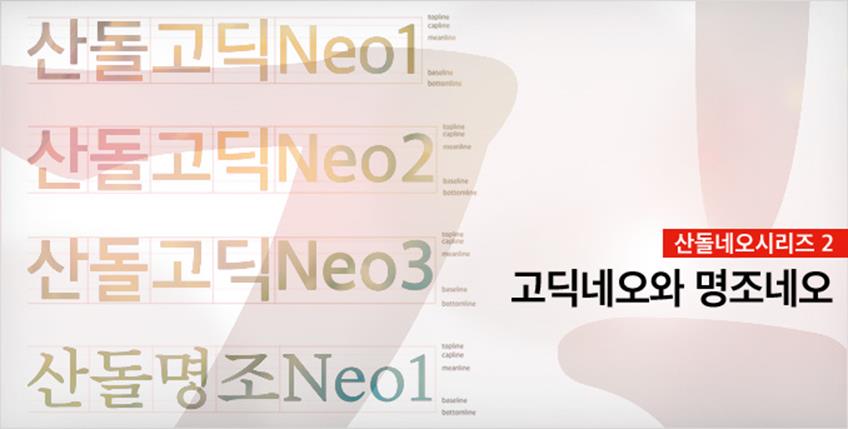
산돌고딕네오1의 컨셉과 특징
산돌고딕네오1은 탈네모가 아닌 네모틀의 한글 활자체이지만 초성, 중성, 종성의 자소들이 네모틀 내부에서 좀 더 자유로워진 형태를 갖추고 있다. 모듈 내부의 검은 글자와 흰 공간이 가지런하게 안배되어 기존 산돌고딕의 고전적인 모습보다 현대적인 이미지를 담고 있다. 또한, 산돌고딕네오1은 편집디자이너들의 요구에 맞추어 정교한 조판을 위한 다양한 웨이트를 제공한다. 그로 인해 합성글꼴 사용시 보다 균정한 지면의 색채감 제공이 가능하다. 다양해진 인쇄환경에 따라 미세한 차이를 고려하여 웨이트를 적용하면 보다 높은 품질의 결과물을 얻을 수 있도록 한 것이다.
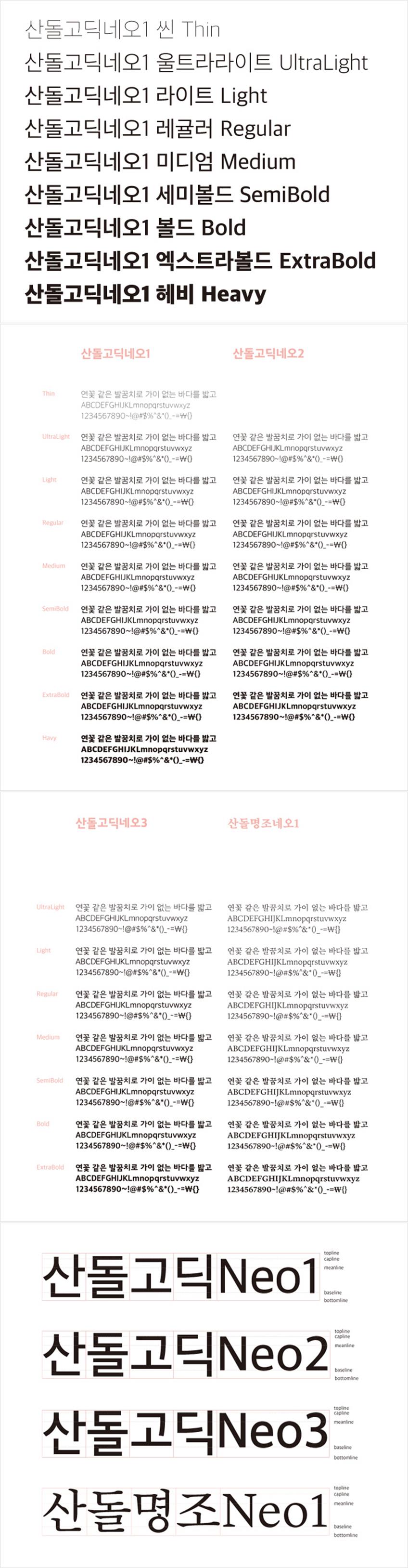
산돌네오시리즈는 산돌고딕네오1, 고딕네오2, 고딕네오3, 명조네오1으로 구성되어 있다.
산돌고딕네오1에는 영국 유력일간지 <The Guardian>의 Guardian Sans Headline을 개발한 커머셜 타입(Commercial Type)으로부터 정식 라이선스를 획득하여 개발한 ‘산돌가디언산스’가 라틴 알파벳 폰트로 포함되어 있다. 산돌가디언산스는 가디언산스 활자체 본래의 성격은 유지하되 한글의 구조와 골격에 잘 어울리도록 각각의 사이즈와 자간을 조정해 시각적 균등감과 조화를 이루어 냈고, 한글과 라틴 알파벳이 서로 고른 무게감을 가지도록 아홉 종 웨이트로 수정되었다.
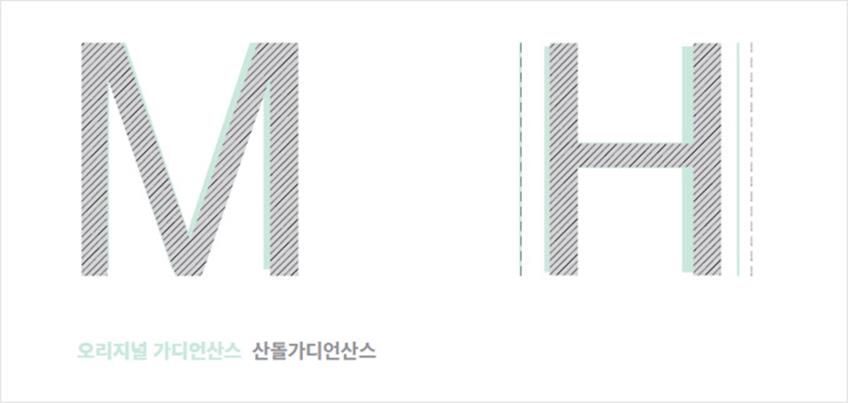
크기(왼쪽 예)는 한글과 시각적으로 균등해 보이도록 라틴 알파벳 크기를 103%로 확대하고, 자간(오른쪽 예)의 경우 가디언산스는 글자폭이 산돌고딕네오1보다 상당히 좁아 사이드베어링을 늘려 넓게 수정했다.
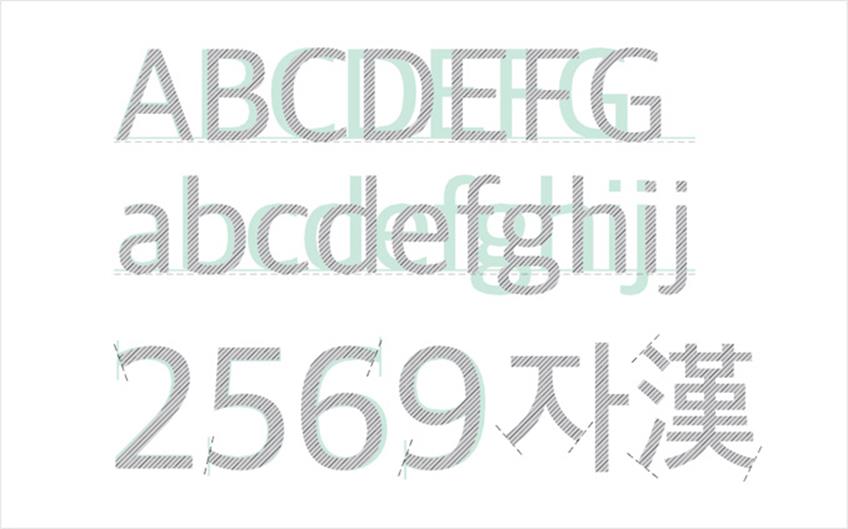
아랫기준선(baseline)을 25유니트 내리고, 숫자는 문장부호와 더불어 한글과 함께 사용하는 빈도가 높아 한국어 조판 환경에 맞추어 가장 많은 수정을 거쳤다. 라틴 알파벳은 획 마감 부분에 있어서 오리지널 형태를 존중했지만 숫자는 획의 진행 방향과 직교하며 마무리되는 한글 디자인의 원칙에 따라 획 마무리 부분 각도를 조정하고 필요에 따라 형태와 폭을 약간 수정했다.
산돌고딕네오2와 고딕네오3의 컨셉과 특징
산돌고딕네오2는 산돌고딕네오1에 구조적인 변화를 주어 네오시리즈에 다양한 표정을 부여했다. 네모틀에서 벗어나 초성, 중성, 종성의 자소들이 탈네모 인상을 풍기도록 했다. 모듈 내부의 검은 글자와 흰 공간을 가지런하게 안배하여 기존 산돌고딕보다 한층 더 밝고 현대적인 이미지가 느껴지도록 한 것이다. 한편, 산돌고딕네오3은 탈네모틀 형태로 초성, 중성, 종성의 자소들이 내부에서 모던한 형태를 보여주며, 산돌고딕네오2 보다 밝고 젊은 모습으로 제작되었다. 또한 구조적인 형태로 인해 글자 아래의 율동감이 살아 있도록 했다.
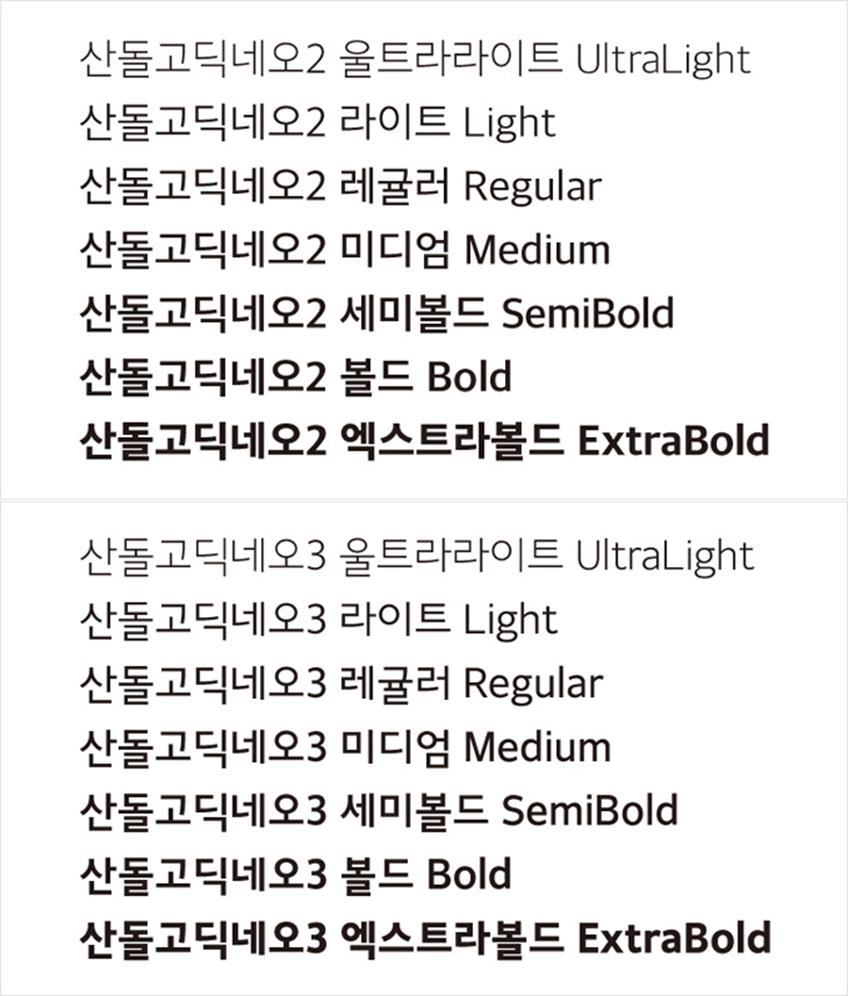
산돌고딕네오2와 고딕네오3는 7종 웨이트로 제작되었다.
산돌고딕네오2와 고딕네오3의 패밀리 웨이트 구성은 기능성에 맞춰 본문용, 중간제목용, 대제목용 등 용도에 따른 굵기 설정과 구조변화가 이루어졌다. 산돌고딕네오1 보다 웨이트 종류가 적어 웨이트 스팩트럼을 더 넓게 가져갔으며, 웨이트 각각의 공간에 따라 획의 구조를 변경하여 패밀리간의 일관성을 유지하면서 균형과 기능을 강화했다. 또한, 산돌고딕네오1과는 달리 산돌고딕네오2와 고딕네오3의 라틴 알파벳은 산돌의 순수 자체 기술로 디자인되어 들어갔다. 한글의 모아쓰기 구조 변화에 따라 라틴 알파벳의 타입페이스를 변화시키고 베이스라인 또한 산돌고딕네오시리즈 변화에 따라 고딕네오1 보다 높게, 고딕네오3은 고딕네오2보다 높게 설정되었다. 산돌고딕네오2와 고딕네오3이 요구하는 밸런스와 일관성이 라틴 알파벳에도 적용된 것이다.
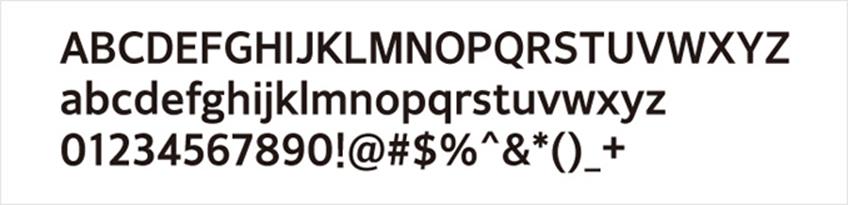
산돌고딕네오2와 고딕네오3의 라틴 알파벳은 산돌의 순수 자체 기술로 디자인되어 탑재되었다.
산돌명조네오1의 컨셉과 특징
산돌명조네오1은 국내에서 디자인되는 책 본문에 많이 쓰이는 명조체의 원류, 최정호 선생의 명조체를 계승하고 이를 현대에 맞게 디자인한 서체다. 한국적 붓 놀림의 아름다움을 담으면서도 돌기와 맺음의 모양을 확실하게 다듬어 단단한 느낌이 들도록 디자인되었다. 본문체의 주요 고려 사항인 가독성, 익숙함, 균형, 요소 간의 통일성, 낱자 간의 조화, 시각중심선의 정렬이 최적화되었다. 또한, 산돌명조네오1은 컨트라스트를 줄이고 기존 본문보다 굵게 다듬고, 자소 크기와 속공간을 키워 현대 인쇄 환경에 맞도록 디자인되었다는 특징이 있다. 결국 가독성을 높인 것이다. 가로 쓰기로 사용될 때 가독성을 높이기 위해 글자 폭을 100%가 아닌 94%로 정하고 공간 안배를 통하여 글자 사이가 고르고 짜임새 있는 조판이 되도록 했다. 가로쓰기에 맞도록 돌기(부리) 각도와 자소 형태 내의 각도를 눕혀 눈이 덜 피로하도록 하고 시각중심선을 위쪽으로 올려서 시선 처리가 편하도록 만들어졌다는 특징도 있다.
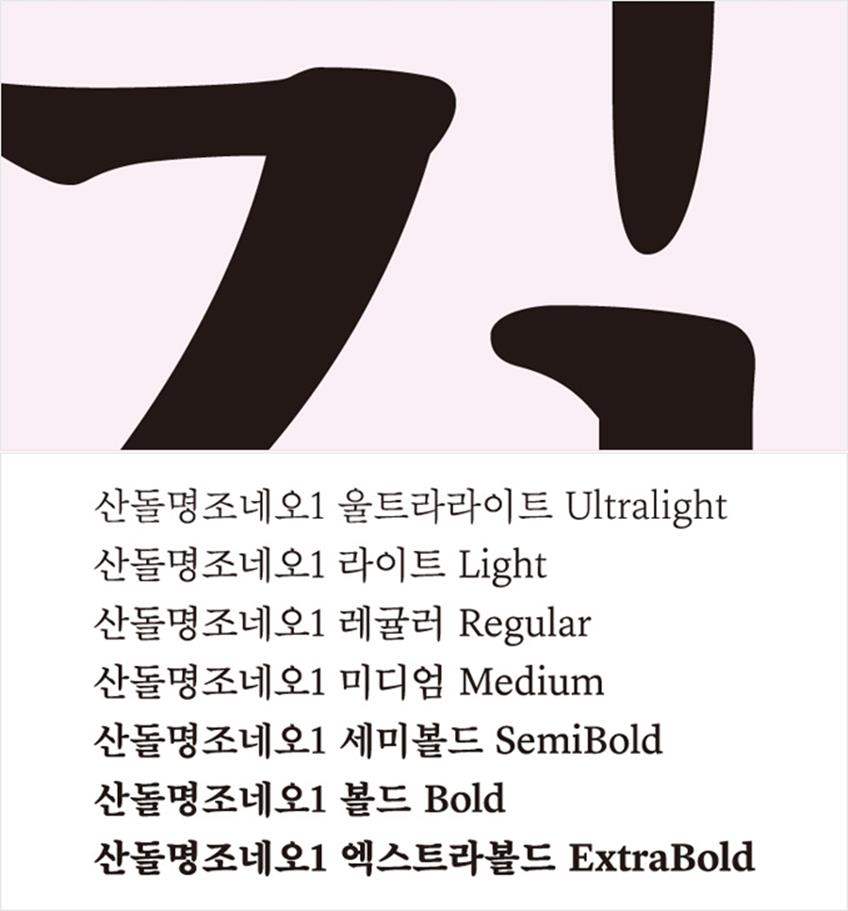
산돌명조네오1의 일곱 가지 웨이트
산돌명조네오1은 7종의 웨이트로 구성되어 있다. 하나의 글자 가족(family)으로서 일관성을 가지는 다양한 웨이트를 제공하여 서체를 사용하는 환경과 필요에 따라 선택할 수 있도록 한 것이다. 각각의 웨이트 특징에 맞춰 다르게 디자인하면서 동시에 하나의 패밀리로 보이는 점도 하나의 특징이다. 산돌명조네오1의 라틴문자로는 커머셜타입(Commercial Type, www.commercialtype.com)으로부터 리옹 텍스트체(Lyon Text) 라이선스를 구입하여 개발한 ‘산돌 리옹’이 적용되었다. 리옹체는 카이 베르나우(Kai Bernau)가 디자인해 커머셜타입에서 발매한 서체로, 에 사용되며 2009년도부터 대중에게 알려지기 시작했다. 리옹 텍스트체는 16세기 식자공 로베르 그랑종(Robert Granjon)의 서체를 현대적으로 재해석한 서체로 로만과 이탤릭으로 구성되어 다섯 가지 굵기를 갖고 있다.
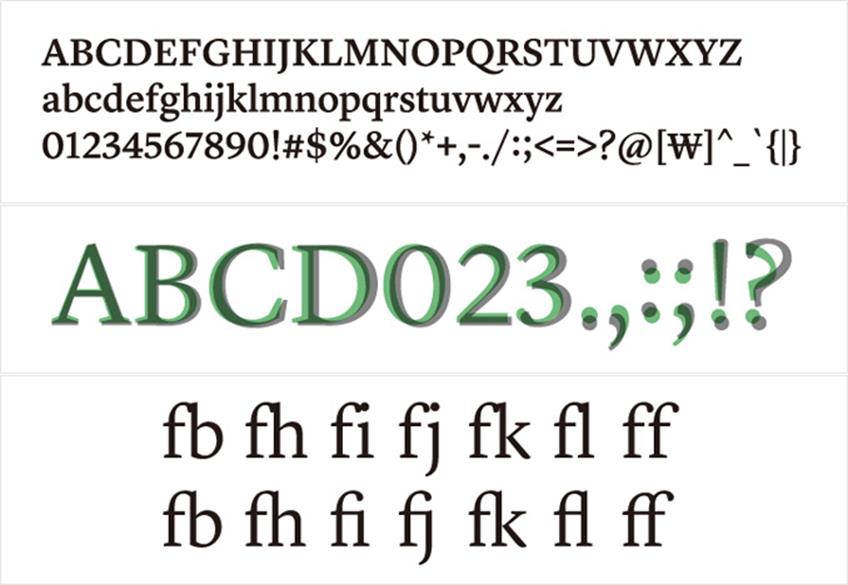
산돌명조네오1에는 커머셜타입에서 리옹 텍스트체 라이선스를 구입하여 개발한 ‘산돌 리옹’이 탑재되었다.
산돌명조네오1에서는 한글 Ultralight 굵기에 맞춰 카이 베르나우와 크리스찬 슈와츠(Christian Schwartz)가 산돌리옹 울트라라이트를 제작했으며 그것을 기반으로 나머지 웨이트의 산돌리옹체가 제작되었다. 산돌리옹체는 산돌고딕네오1의 ‘산돌가디언산스’와 같이 리옹체 본래의 성격은 유지하되 한글 환경에 맞춰 굵기, 크기, 위치, 몇 가지 세부 디자인이 재조정되었다. 또한 13개의 리가쳐(ligature)와 커닝 값을 각각 웨이트에 맞게 넣어 조판에 문제가 없도록 했다.